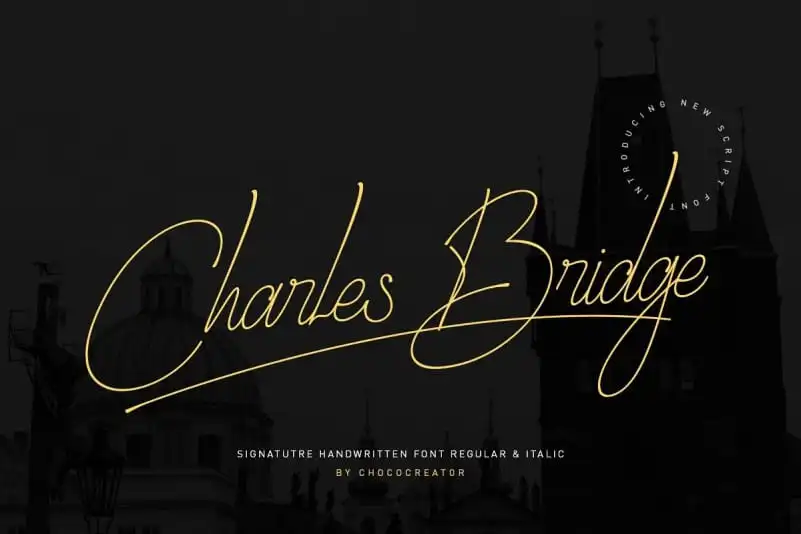
A ‘Charles Bridge Handwritten Font’ é uma elegante tipografia escrita à mão, criada pelo designer Chococreator. Perfeita para qualquer aplicação que valorize estilo e sofisticação, ela se destaca com seu ar despojado e moderno. Ideal tanto para criações de marca quanto cartões de casamento e cartas, esta fonte escrita à mão também traz uma vibe interessante para rótulos de vinho. Com sua personalidade única, a ‘Charles Bridge Handwritten Font’ oferece aos designers um recurso refinado para dar ao seu design um toque elegante e pessoal. Não importa se você está trabalhando em cartões promocionais de uma marca, cartas íntimas ou até mesmo rótulos de vinho, esta fonte escrita à mão proporcionará a perfeição que tanto busca. Ela é uma escolha inteligente para quem procura um estilo elegante e sofisticado que também expressa uma ligação direta com o usuário final.